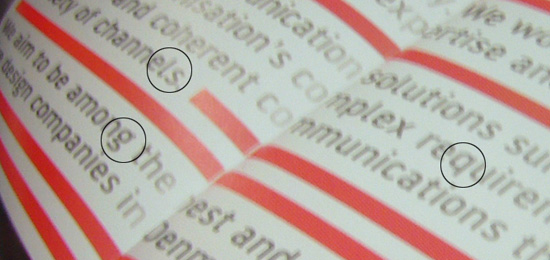
kennt jemand diese Schrift?
kennt jemand diese Schrift? leider ist die Abbildung unscharf,
auffällig ist das g, das l, die geringen Ober- und Unterlängen
und die geringe Versalienhöhe – danke euch für Hinweise!
Ich würde mal behaupten, dass es die Trebuchet MS ist. Liegt dem Internet Explorer bzw. den MS Office Paketen bei.